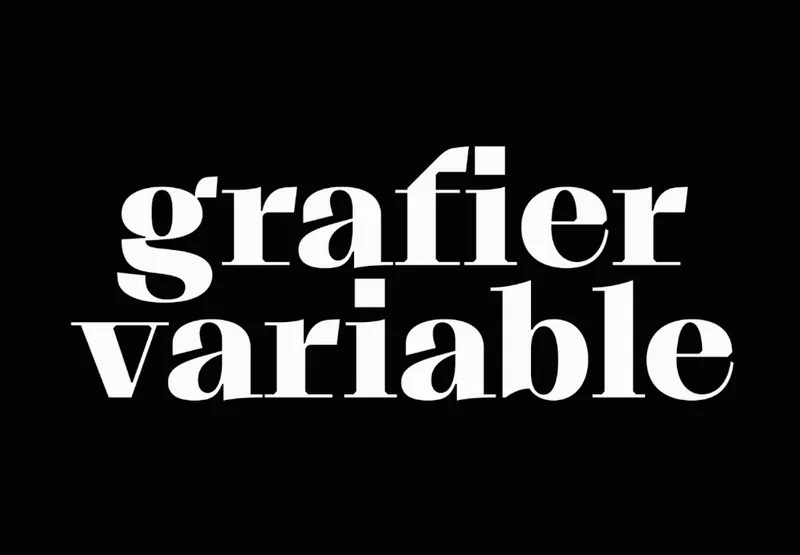
Aqui está uma descrição em português do Brasil, envolvente e natural, para a página de download da fonte ‘Grafier Serif Font Family’, seguindo as instruções fornecidas: Para os amantes de um charme vintage ou aqueles que buscam criar logomarcas elaboradas à mão, a Grafier é uma ótima escolha. Esta fonte séria vem em família e oferece uma elegância clássica para projetos digitais contemporâneos. Inspirada nos tradicionais tipos serif, como o Baskerville dos anos 1800, a Grafier captura um toque fresco e preciso que combina elementos da arte manual com as curvas de computador. O resultado é uma fonte que se adapta bem tanto para textos legíveis quanto para designs elegantes. Para maximizar seu uso criativo, o designer Hamilton incorporou alternativas estilísticas em OpenType que permitem separar cada letra do conjunto. Além disso, a família vem em cinco pesos de negrito e duas medidas ópticas – um texto levemente maior e uma configuração exibicional mais sofisticada. Com Grafier, você pode criar interfaces digitais que rompem as barreiras entre o cotidiano e os ambientes de arte. Com seu formato variável, é possível explorar infinitas possibilidades criativas, permitindo que cada caracter apareça de uma maneira única, dando ao design um toque moderno de originalidade. A Grafier é uma opção perfeita para aqueles buscando uma mistura arredondada e contemporânea que transcende o tempo.